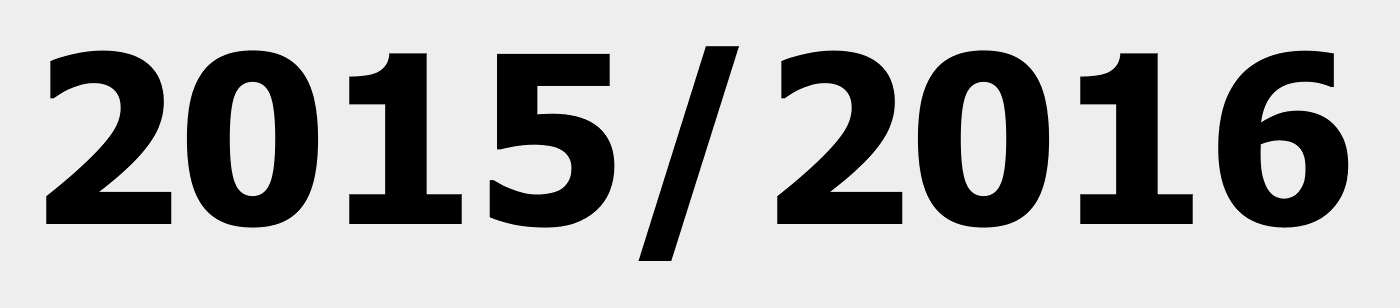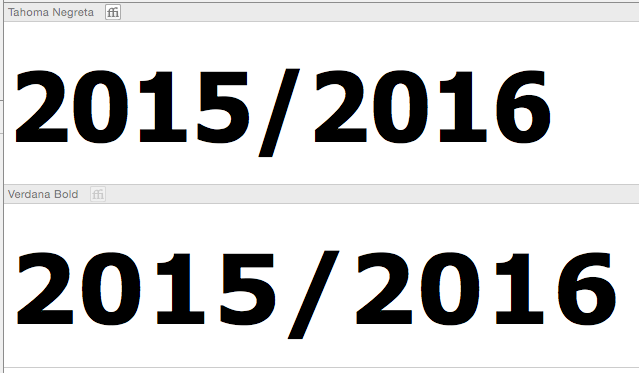
Suche Schrift aus einem Logo
weiß jemand welche Schrift das ist? Wurde mir netterweise in Pfade übergeben.
Tahoma würde ich weniger spontan sagen.
Die 6 ist bei der Tahoma ein klein bisschen schmäler als bei der Verdana.